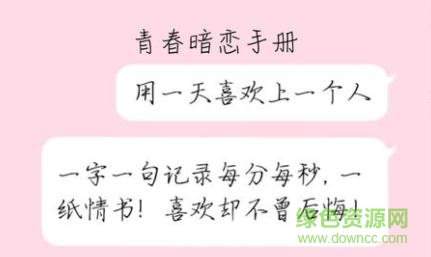
青春暗戀手冊字體
青春暗戀手冊ttf是一款小清新的手寫書法字體,這款字體給人的感覺就像是暗戀的感覺,非常要想表達自己但是又很含蓄,感興趣的朋友歡迎下載使用!
青春暗戀手冊ttf簡介
青春暗戀手冊ttf是一款提取自qq中的手寫字體,這款字體看上去非常的娟秀,并且連筆處理的非常漂亮,整體看上去會非常的賞心悅目!